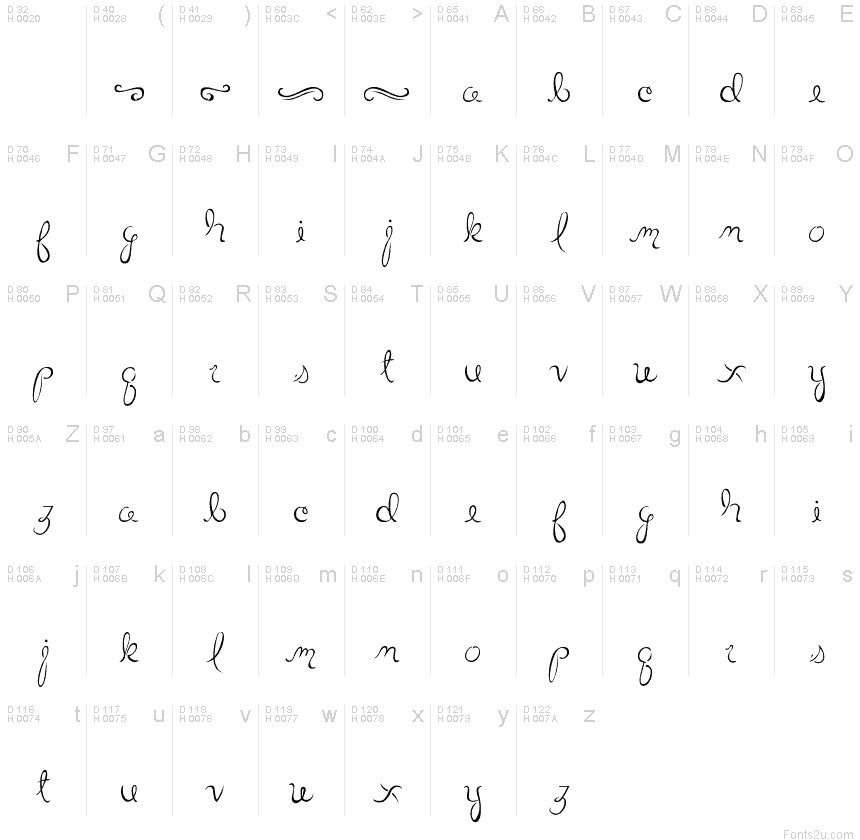
Little Bliss، من تصميم Dirt2.com، هو خط كتابة يدوي مجاني يتميز بعروات عالية ومرسومة بدقة، وارتفاعات حادة، وطابع أنيق وعصري. تنساب حروفه الضيقة في حركة واحدة سريعة ومستمرة.
تعد دعوات الزفاف بيئته المثالية، إذ تشبه الحركات المنسابة والزخارف الكبيرة خط اليد الشخصي ولكنها تتمتع باتزان وهدوء الخط الرسمي. تناسب نفس الأشكال الخفيفة والممتدة العلامات التجارية للبوتيكات، وتعبئة مستحضرات التجميل الفاخرة، ومجلات الموضة، حيث يمكن للحروف أن تحاكي خطوط الأشرطة الدقيقة أو الرسوم التوضيحية الرقيقة بالحبر.